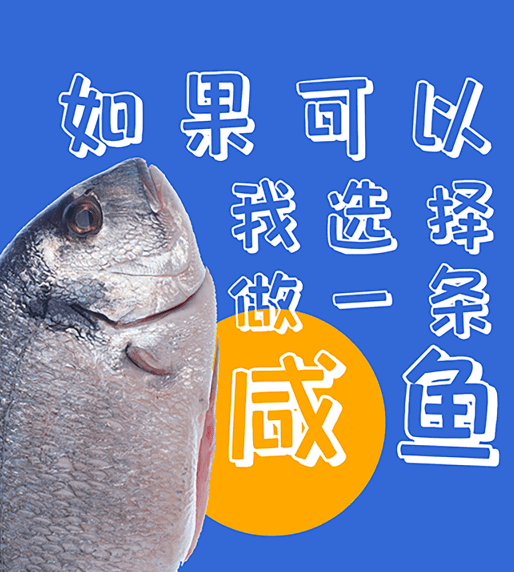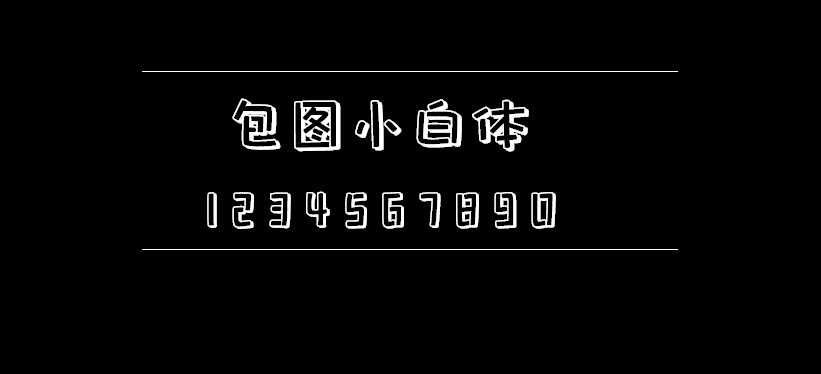
包图小白体
包图小白体,一款简单可爱的创意字体。在字形笔画上去除了折笔的弧形,换之以平直的笔画,竖弯钩转为竖折,同时弱化了钩笔画,省去了许多笔画末尾的小尾巴,显得更加直白可爱。粗短的笔画,像柯基的小短腿,相比细长的字体能给人更多的轻松感。整体形态采用了镂空的制作技巧,增强了字体的立体感,适合用于品牌标志、海报、包装、影视综艺、 游戏、漫画等场景。